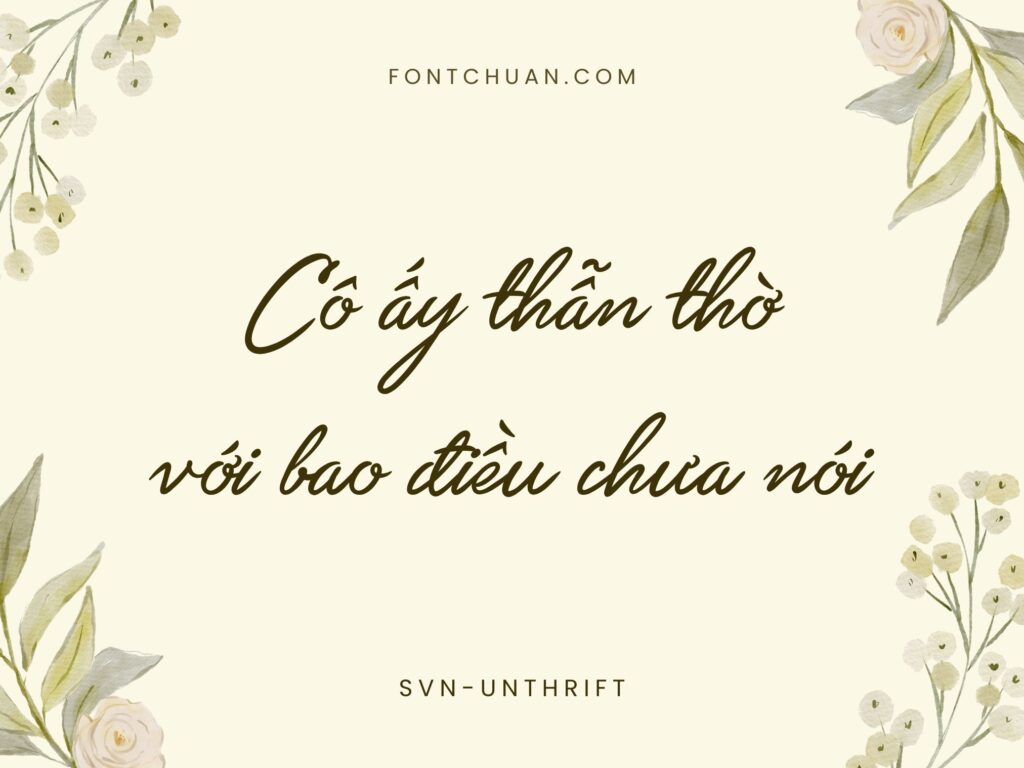
Font SVN Unthrift Việt Hóa
Tác giả Font: Måns Grebäck
Font SVN-Unthrift là phiên bản Việt hóa của kiểu chữ Unthrift, được thực hiện bởi Styleno.1 Fonts. Unthrift là một kiểu chữ script chất lượng cao, được tạo ra bởi Måns Grebäck vào năm 2015. Font này được xây dựng với các nét cọ lớn và sống động, lấy cảm hứng từ chữ viết tay những năm 1990. Unthrift bao gồm hai phiên bản, First và Second, mỗi phiên bản có một bộ ký tự khác nhau, cùng với các chữ cái thay thế, chữ cái kết thúc, chữ cái bắt đầu và nhiều ligature, giúp tạo ra hàng nghìn khả năng tùy chỉnh trong thiết kế. ([svnfont.com](https://www.svnfont.com/viet-hoa-svn-unthrift/?utm_source=chatgpt.com))
SVN-Unthrift lý tưởng cho các dự án thiết kế yêu cầu sự cá nhân hóa và tinh tế, như thiệp mời, logo, tiêu đề và các ấn phẩm truyền thông. Các ngành nghề như thiệp cưới, ẩm thực và spa có thể tận dụng font này để tạo điểm nhấn trong thiết kế. Ngoài ra, font cũng thích hợp cho các sự kiện như Tết, Valentine, Sinh nhật và các lễ hội khác.